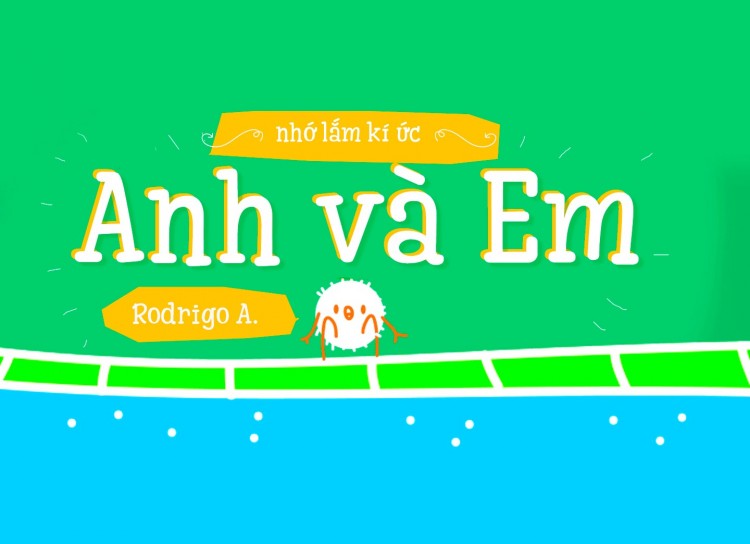
Trong thế giới đồ họa hiện đại, việc lựa chọn một bộ Font Chữ phù hợp là yếu tố quyết định sự thành công của một bản thiết kế. Font việt hoá iCiel Cucho nổi lên như một sự lựa chọn hàng đầu cho các bạn học sinh và giáo viên khi cần tạo ra các ấn phẩm học đường sinh động. Với đường nét mềm mại nhưng vẫn giữ được sự chắc chắn, bộ phông này mang lại cảm giác thân thiện và dễ gần cho người xem.
Khám phá đặc điểm nổi bật của Font việt hoá iCiel Cucho
Thiết kế độc đáo và linh hoạt
Bộ Font việt hoá iCiel Cucho được cộng đồng thiết kế tại Việt Nam yêu thích nhờ phong cách trẻ trung và đầy tính sáng tạo. Điểm đặc biệt của phông chữ này nằm ở cấu trúc các ký tự được bo tròn khéo léo, giúp nội dung trở nên bắt mắt và không gây nhàm chán. Đây là công cụ đắc lực để thiết kế các bìa sách, poster sự kiện trường học hoặc những trang slide bài giảng thêm phần cuốn hút và chuyên nghiệp hơn bao giờ hết.
Khả năng hiển thị tiếng Việt hoàn hảo
Một trong những ưu điểm lớn nhất của Font việt hoá iCiel Cucho chính là việc tối ưu hóa hoàn toàn các dấu câu tiếng Việt. Người dùng sẽ không còn lo lắng về lỗi font hay các ký tự bị nhảy dấu khi soạn thảo văn bản. Điều này đặc biệt quan trọng trong giáo dục, giúp các em học sinh dễ dàng tiếp cận kiến thức qua những khung hình chữ đẹp mắt, chuẩn chỉnh và dễ đọc trên cả màn hình máy tính lẫn bản in giấy.
Để tận dụng tối đa vẻ đẹp của bộ chữ này, bạn nên kết hợp nó với các tông màu tươi sáng hoặc pastel để tạo nên sự hài hòa cho tổng thể. Font việt hoá iCiel Cucho không chỉ đơn thuần là một bộ ký tự, mà còn là nguồn cảm hứng cho những ý tưởng thiết kế đột phá. Nếu bạn đang tìm kiếm Font Miễn Phí, Font Việt Hóa, Font việt hoá iCiel Cucho để làm mới dự án của mình, hãy tải ngay về máy để trải nghiệm sự khác biệt mà nó mang lại cho tác phẩm của bạn.